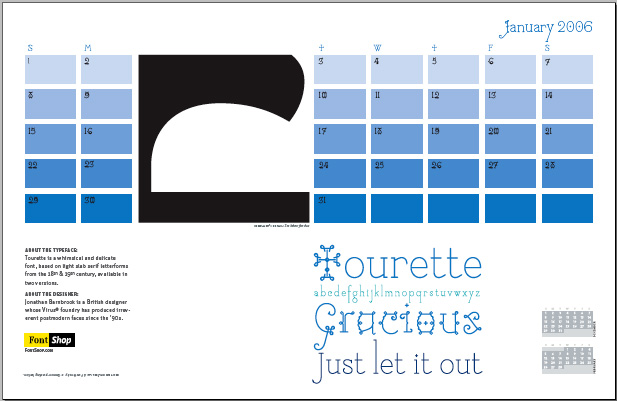
vorbereiteter Wallpaper. Diesmal beschränkt sich die Auswahl der Schriften
nicht auf eine Bibliothek, sondern wir mischen interessante Fonts
unterschiedlicher Quellen. Den Januar reichen wir heute nach, zusammen mit dem
Für die Gestaltung des Januar-Kalenderblattes griffen unsere Gestalter
zur Schrift Tourette von Virus. Es ist eine skurrile Slab-Serif mit zwei
Stilvarianten: einem leichten Normalschnitt und einem verschnörkelten
»Extreme«-Variante.